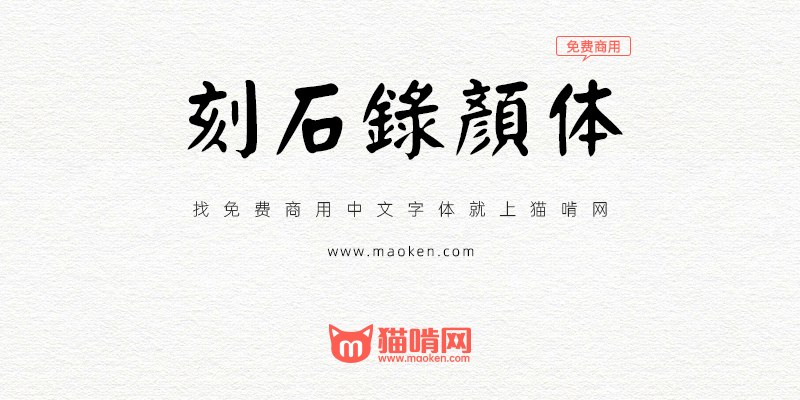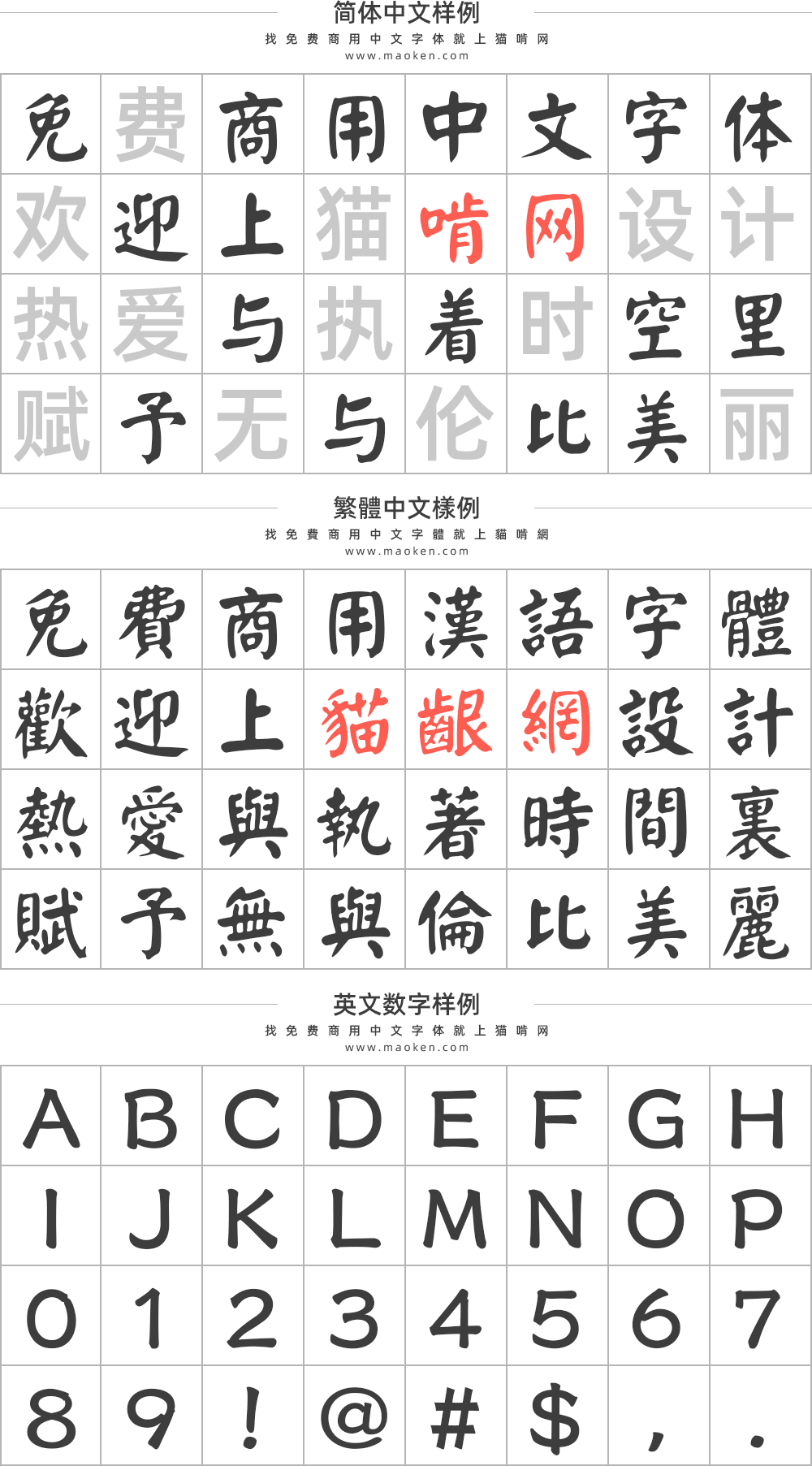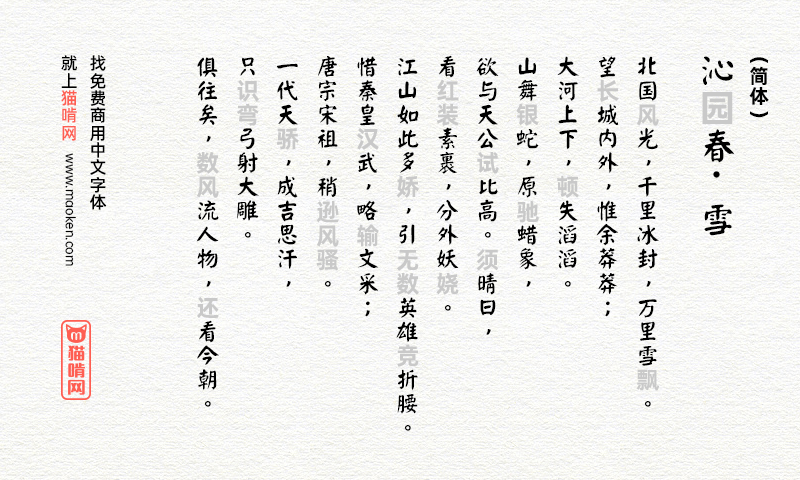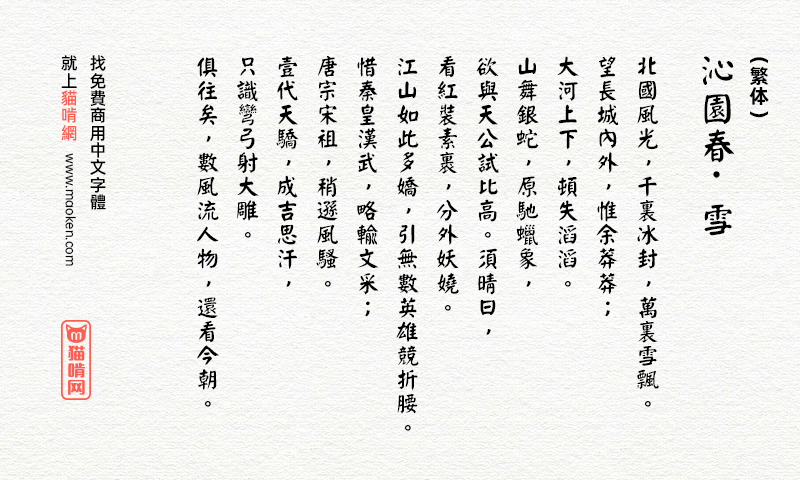
刻石录颜体:基于王汉宗颜体修改而成的颜体楷书
字体作者:刻石录(中国台湾) 字体字重:1个
字体背景介绍
目前中文开源字体尚少,犹幸还有一些有心人士,就如王汉宗敎授。王敎授乃台湾中原大学数学系敎授,当年天蚕中文字库正由他硏发。他先后在2000年和2004年,捐出共42套字型作开源使用,全部均以GNU GPL分发。
可惜于2005年,文鼎公司认为王敎授的部份字型与它们的商业字型有形似的争议。爲了避免法律纠纷,各开源网站都把王老师的字型下架。而所谓的法律纠纷,至今并无公开的结果。
早前,Justfont经专业的比对和硏究,证实王敎授的一些字体,并不涉及与文鼎字型的版权纠纷,可以放心使用。Justfont把这批安全的王敎授字体,遵从GNU GPL条款,免费提供给大家。
刻石录网站选择了当中的粗钢体,重新制作和修整原字型中缺少的或有欠美观的部份,例如半形英数、圈圈字、常用符号等,就成为了现在这部刻石录钢笔鹤体。
• 修正Mac作業系統的支援問題。鑑於字型家族名字須以字母作開首,故把名字由「1.顏體」改作「I.顏體(I.Ngaan)」,「I」即羅馬數字「1」。
• 取得開源字體「王漢宗顏體(HanWangYanKai)」wt064.ttf,字體以GNU GPL 2.0或以上授權條款發佈。
• 然而是基于王汉宗字体改的,王汉宗颜体与华康颜楷相似度很高。